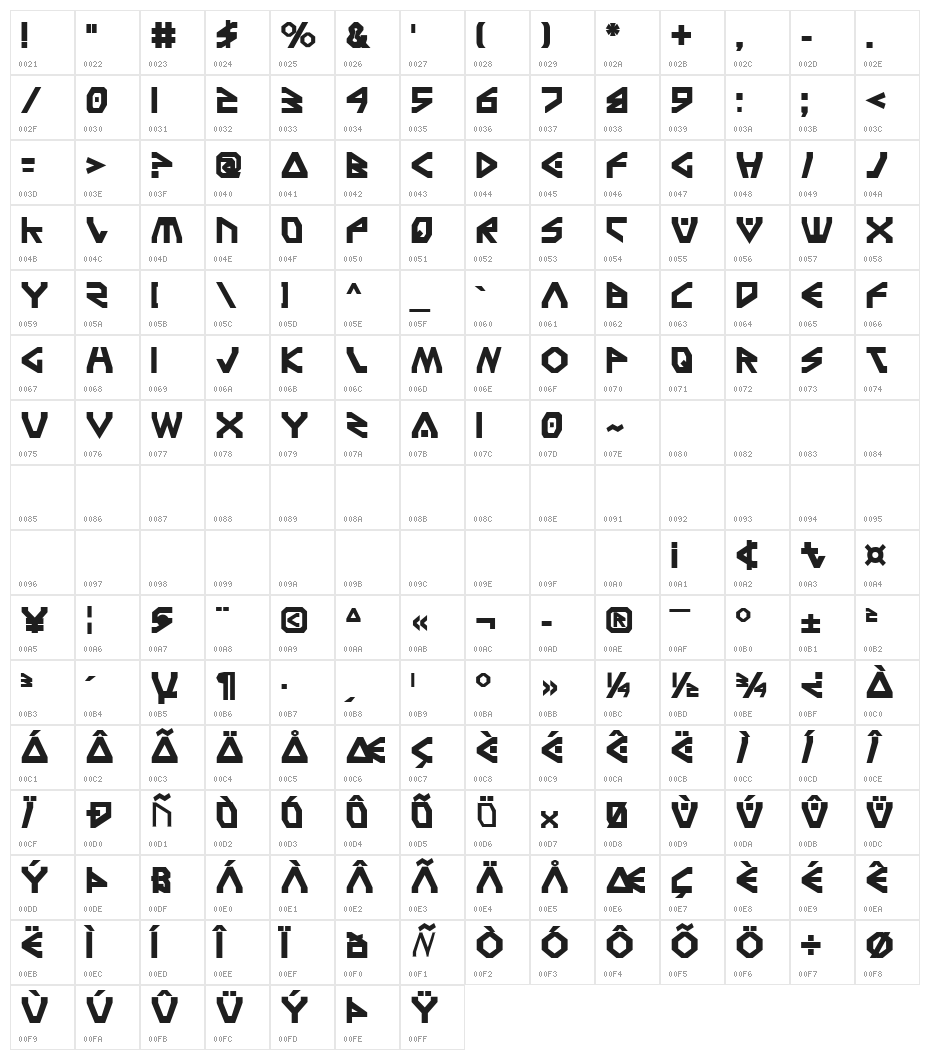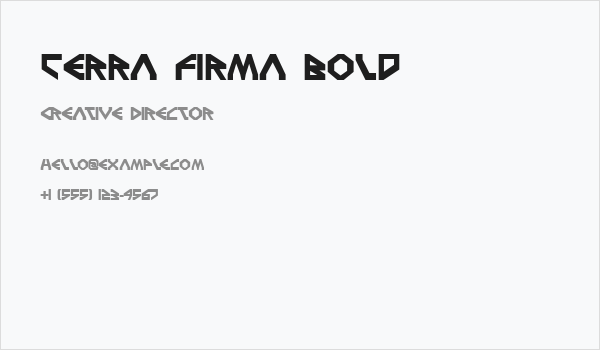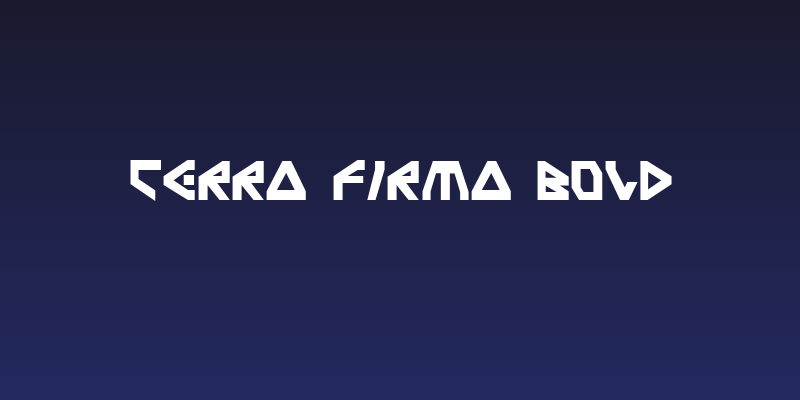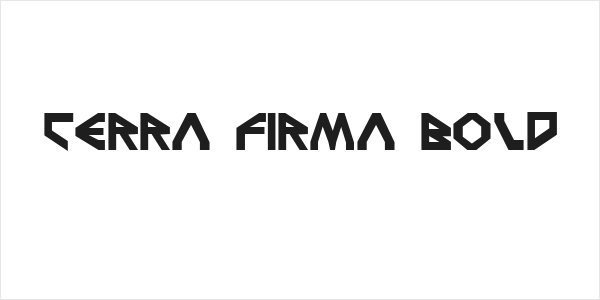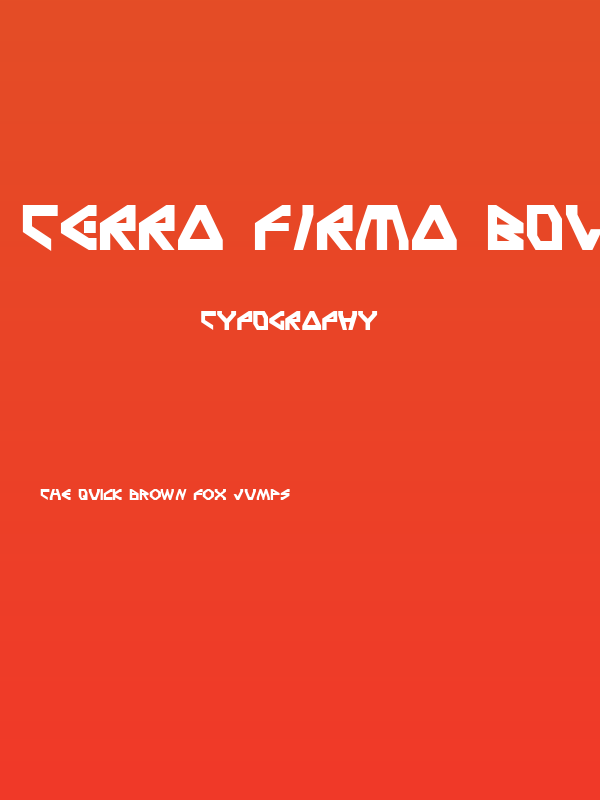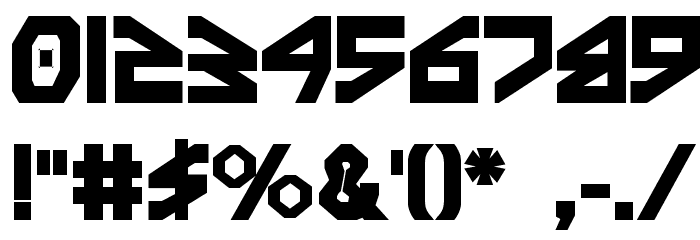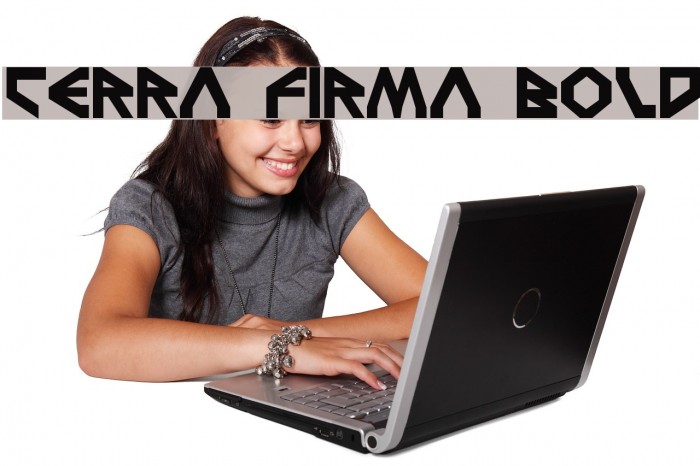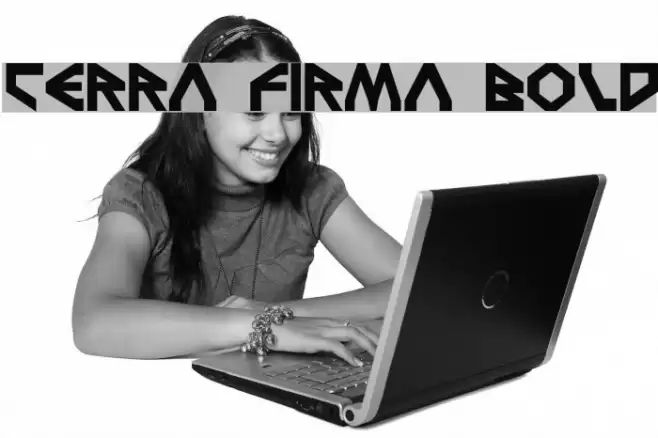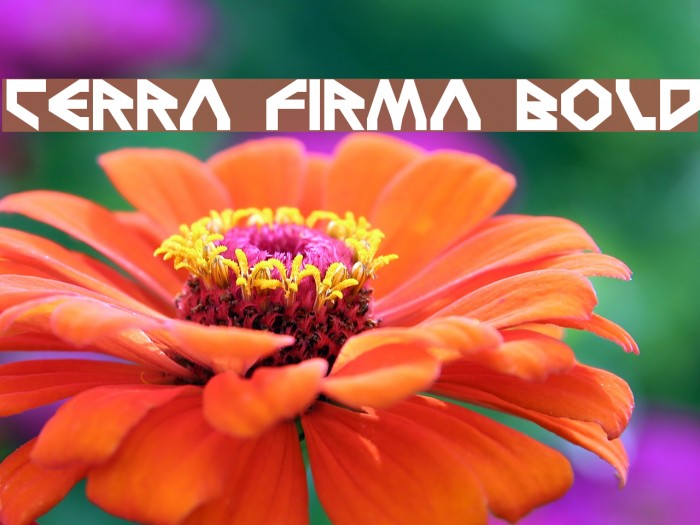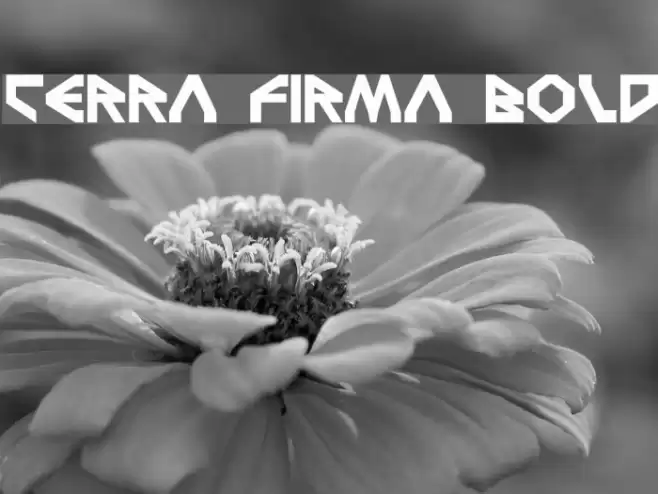
Terra Firma Bold Font
| Projets proposés | Ideal for sci-fi themed designs, video game graphics, posters, and branding that requires a modern and bold statement. |